Font phấn viết bảng Việt hóa là nhóm phông chữ đặc thù mô phỏng chân thực vệt ma sát của viên phấn trắng trên nền bảng đen thô nhám, nổi bật với các hạt bụi phấn li ti, đường viền xước mờ và nhịp điệu vẽ tay mộc mạc. Mang vẻ ngoài hoài niệm, thân thương và đậm tính thủ công, font chữ phấn viết bảng Việt hóa là chất liệu trực quan tuyệt vời để các kiến trúc sư, nhà thiết kế mang lại sự ấm áp cho các bản vẽ phối cảnh quán cà phê phong cách bistro, trường mầm non lắp ghép hay các bảng thực đơn lưu động.
Vệt bụi phấn thô sần và cảm xúc hoài niệm của font phấn viết bảng Việt hóa
Điểm cuốn hút của font phấn viết bảng Việt hóa nằm ở sự bất đối xứng tự nhiên và độ đậm nhạt không đồng đều giữa các nét kéo bút, tái hiện cảm xúc chân thực của những giờ giảng bài nơi lớp học xưa. Các hạt mực kỹ thuật số được phân bổ rải rác mô phỏng hoàn hảo kết cấu bụi phấn bám trên thớ gỗ sơn đen, loại bỏ hoàn toàn vẻ nhẵn nhụi của các kiểu chữ in ấn phẳng.
Sự ổn định về mặt cảm xúc của dòng font này giúp khơi gợi tình cảm ấm áp, sự mến khách và bầu không khí sinh hoạt gia đình bình dị. Khi kết hợp cùng các vật liệu kiến trúc cổ điển như vách gỗ thông cháy xơ, tường ốp gạch men thẻ trắng, sàn gạch bông cổ hay khung cửa sổ sắt sơn đen trong các căn nhà container sáng tạo, phông chữ phấn viết bảng tạo nên sự tương thích thẩm mỹ đầy thư thái.
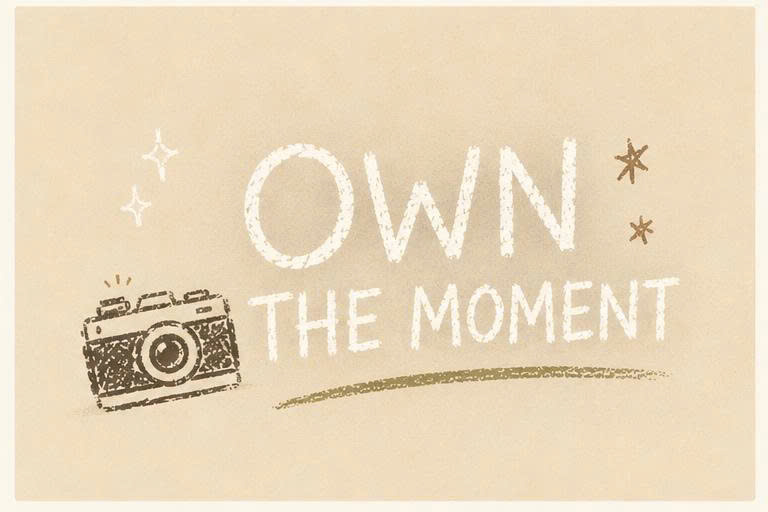
Hồ sơ tài nguyên bao gồm đa dạng các biến thể từ nét phấn thanh mảnh, phấn nét đậm đà đến phông chữ in hoa trang trí (Chalkboard Display). Dưới đây là bảng thông số chi tiết để bạn tham khảo trước khi cài đặt.
Tư vấn từ chuyên viên: Font chữ phấn viết bảng sở hữu kết cấu hạt nhám tự nhiên. Để bản thiết kế đạt hiệu quả thẩm mỹ tốt, bạn nên sử dụng phông chữ này cho các đề mục món ăn, lời chào đón hoặc các câu trích dẫn phong cách sống ngắn.
03 Ứng dụng Font phấn Việt hóa vào công trình thực tế
Nhờ vẻ ngoài bình dị và tính gợi cảm xúc thân thương, bộ phông chữ này mang lại giá trị thực tế lớn trong khâu tạo điểm nhấn cho các công trình hiện đại:
- Bảng Menu treo tường cho Quán Cafe và Tiệm Bánh Container: Những con chữ bụi phấn trắng rất ăn ý khi in UV trên các tấm tôn sơn đen mờ hoặc bảng gỗ công nghiệp dán decal phấn, mang lại diện mạo mộc mạc và cảm giác đồ uống được pha chế thủ công tận tâm.
- Hệ thống biển tên lớp và Góc sinh hoạt Trường mầm non Lắp ghép: Phông chữ này khi dùng làm bảng thông tin, thời khóa biểu hoặc tên góc sáng tạo sẽ giúp không gian học đường toát lên vẻ ấm áp, tạo sự hào hứng cho các bạn nhỏ mỗi ngày đến trường.
- Trang trí không gian bếp ăn Homestay nghỉ dưỡng: Bạn có thể dùng Font phấn Việt hóa để làm tranh chữ trích dẫn công thức nấu ăn, bảng nhắn gửi gia đình, tạo bầu không khí sum vầy và thoải mái cho du khách lưu trú.
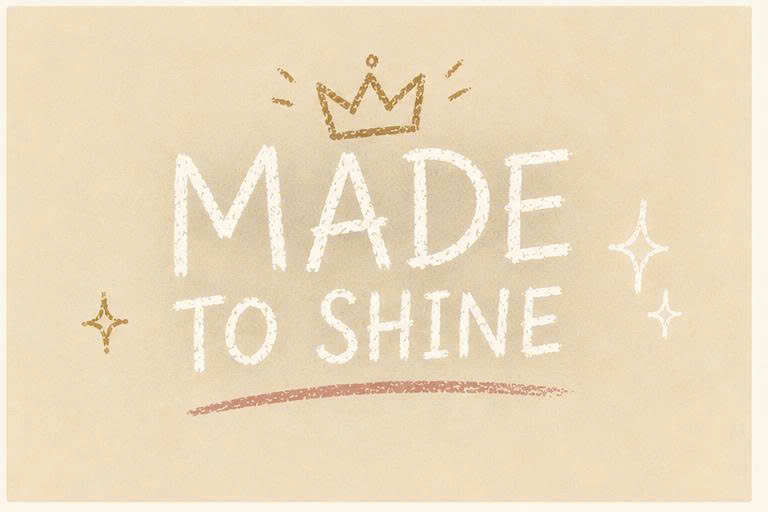
03 Lưu ý bố cục font phấn viết bảng luôn sinh động và rõ nét
Để khai thác hiệu quả vẻ đẹp của dòng font nét phấn thô mộc này mà không gây cảm giác nhem nhuốc cho bản vẽ, người thiết kế nên lưu tâm một số kinh nghiệm sau:
- Ưu tiên đặt trên nền tối màu: Font chữ phấn phát huy hiệu quả thị giác cao khi đặt trên các nền màu sẫm như đen bảng, xanh rêu đậm, xám than chì hoặc nâu gỗ tối, giúp các hạt bụi phấn trắng sáng được hiển thị tách bạch.
- Kiểm soát kích thước khi in ấn: Do các nét xước bụi phấn có cấu trúc hạt rải rác, bạn nên in ấn ở kích thước chữ từ 14pt trở lên để các chi tiết xơ hạt không bị máy in làm nhòe thành vệt mực mờ đục.
- Bố trí khoảng cách dòng: Bạn nên thiết lập khoảng cách dòng thoáng đãng một chút (khoảng 1.4 – 1.5 lần cỡ chữ) để các dấu thanh tiếng Việt không bị chồng lấn vào các hạt bụi phấn của dòng phía trên.
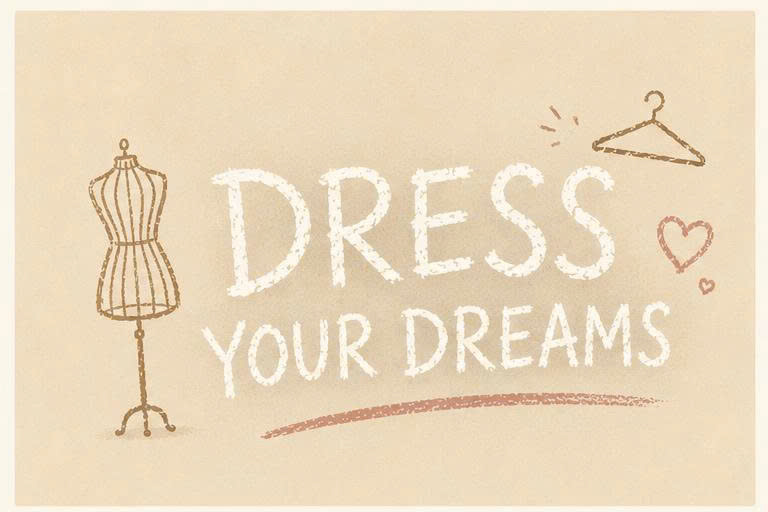
FAQs – Thắc mắc thường gặp khi sử dụng phông chữ phấn viết bảng
1. Font chữ phấn viết bảng có dùng được trên ứng dụng Canva không?
2. Phông chữ này có hỗ trợ đầy đủ các ký tự số và dấu câu không?
Có. Bộ phông chữ phấn viết bảng đã được tích hợp đầy đủ hệ thống chữ số và các ký tự đặc biệt với kết cấu bụi phấn đồng điệu, rất thuận tiện cho việc trình bày bảng giá đồ uống hay phân loại phòng học.